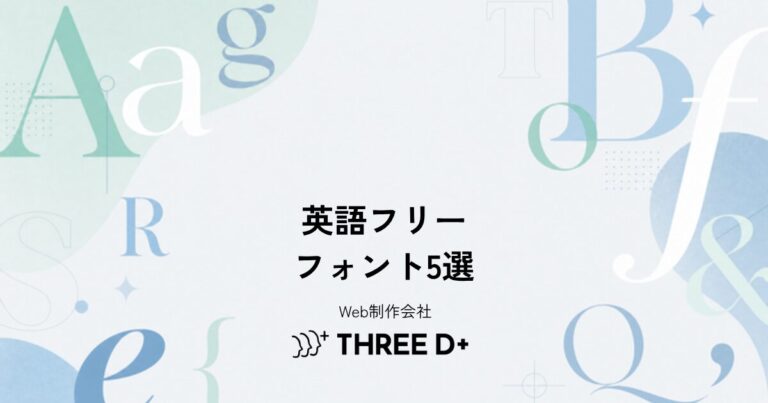
Webデザイナーが実務で使う英語フリーフォント5選【商用利用OK】
Webデザインで使う英語フリーフォントとは、見出しやロゴ、数字表記などに使われる無料のアルファベット書体のことです。フォント一つで印象は大きく変わるため、選び方を知っておくとデザインの完成度が一段上がります。この記事では、Web制作の現場でよく採用される英語フリーフォント5つを、特徴や向いている用途とあわせて紹介します。
なぜ英語フォント選びがデザインの完成度を左右するのか
日本語サイトであっても、見出しの英字部分やロゴ、価格表記には英語フォントが使われる場面が多くあります。日本語フォントは文字の形が複雑なぶん個性を出しにくい一方、英語フォントはアルファベットの形状だけでブランドの雰囲気を大きく左右できるのが特徴です。同じレイアウトでも、使うフォント次第で「洗練された印象」にも「安っぽい印象」にもなり得ます。だからこそ、目的に合ったフォントを知っておくことは、Web制作において重要なスキルの一つです。
実務でよく使われる英語フリーフォント5選
ここでは、Googleフォントを中心に、実務での採用実績が多い英語フリーフォントを5つ紹介します。いずれも商用利用が可能で、Webフォントとしても手軽に導入できます。
Poppins(ポピンズ)
Poppinsは、シルエットが正方形に近いジオメトリックなサンセリフ体です。小文字の「a」や「g」など丸みのある文字が特徴的で、親しみやすさとモダンさを両立できます。Thin〜Blackまで幅広いウェイトが揃っているため、見出しから本文まで1書体で統一感を出したいときに重宝します。コーポレートサイトからカジュアルなLPまで、幅広い案件で使いやすいオールラウンダーです。
Josefin Sans(ジョゼフィン・サンズ)
Josefin Sansは、1920年代のジオメトリックデザインを思わせる、細身で上品な印象のサンセリフ体です。文字の高さに対して横幅が狭めに作られており、洗練された雰囲気を演出できます。美容系・ファッション系・ブライダル系など、上質感やエレガントさを打ち出したいサイトのロゴや見出しと相性が良いフォントです。
Krona One(クロナ・ワン)
Krona Oneは、無骨で力強い印象を持つボールド体のフォントです。文字の太さが均一で視認性が高く、キャッチコピーやセクションタイトルなど、遠目からでも目を引かせたい要素に向いています。ウェイトは1種類のみとシンプルですが、そのぶん迷わず使えるのも実務では嬉しいポイントです。
DIN 2014
DIN 2014は、ドイツの工業規格に由来する、数字表現に強いフォントです。数字の視認性が高く、桁数の多い数字でも読み間違えにくいため、価格表記や統計データ、料金表などとの相性が抜群です。無機質で機能的な印象があるため、テック系・製造業系サイトの数字まわりにもよく使われます。
The Signature
The Signatureは、手書きのサイン風のスクリプト体フォントです。ロゴやアクセントとして一部分に使うだけで、手作り感や特別感を演出できます。主張が強いフォントのため、本文や大量のテキストには不向きですが、キャッチコピーの一部やブランドロゴのワンポイントとして使うと効果的です。
フリーフォントを選ぶときのチェックポイント
フォントの組み合わせ方・使い分けのコツ
実務では、1サイトにつき英語フォントを1〜2種類に絞るのが基本です。見出し用に印象の強いフォント(Krona OneやThe Signatureなど)、本文や数字表記用に視認性の高いフォント(PoppinsやDIN 2014など)というように役割を分けると、デザインに一貫性が生まれます。日本語フォントとの組み合わせでは、英字部分だけを英語フォントに置き換える「フォントの部分適用」を行うと、和文と欧文のバランスが取れた、見栄えの良い仕上がりになります。
Q. Web制作でフォントは何種類まで使ってよいですか?
A. 一般的には英語フォント1〜2種類、日本語フォントと合わせても3〜4種類程度に収めるのが目安です。使いすぎるとデザインの統一感が失われやすくなります。
まとめ